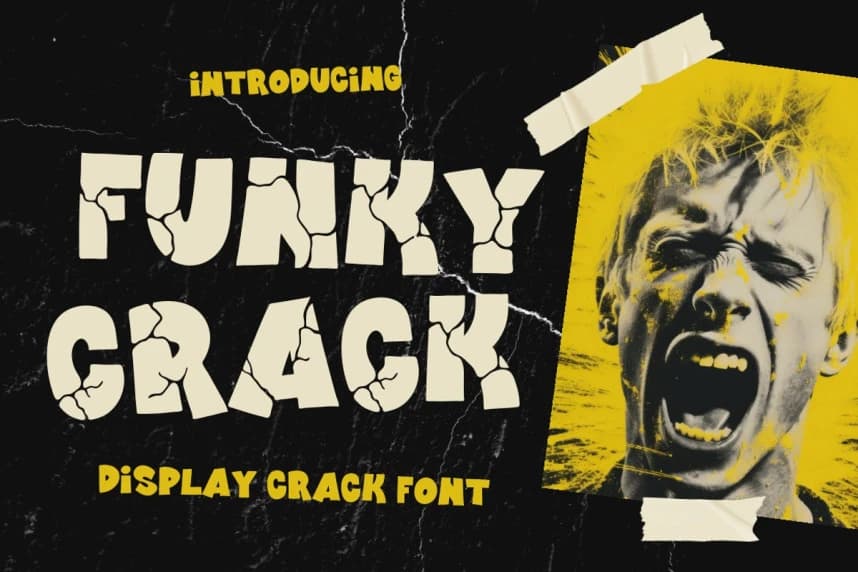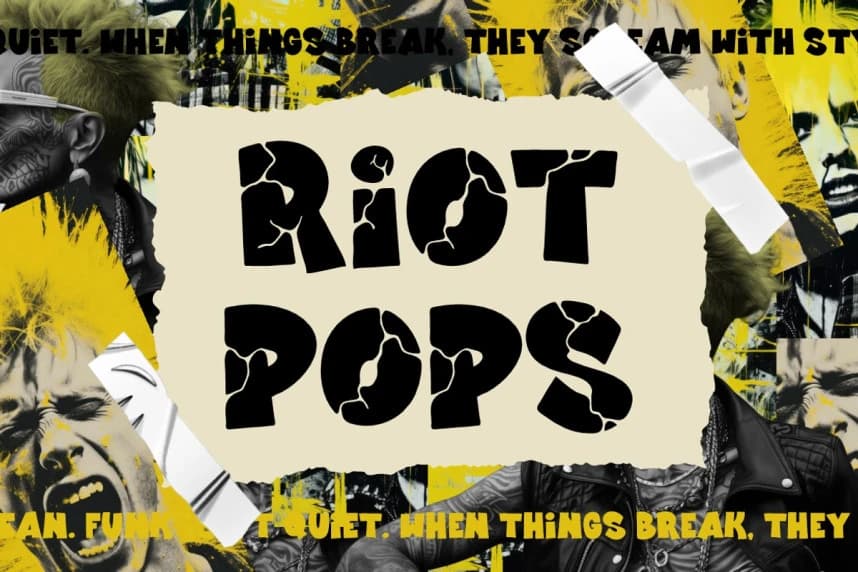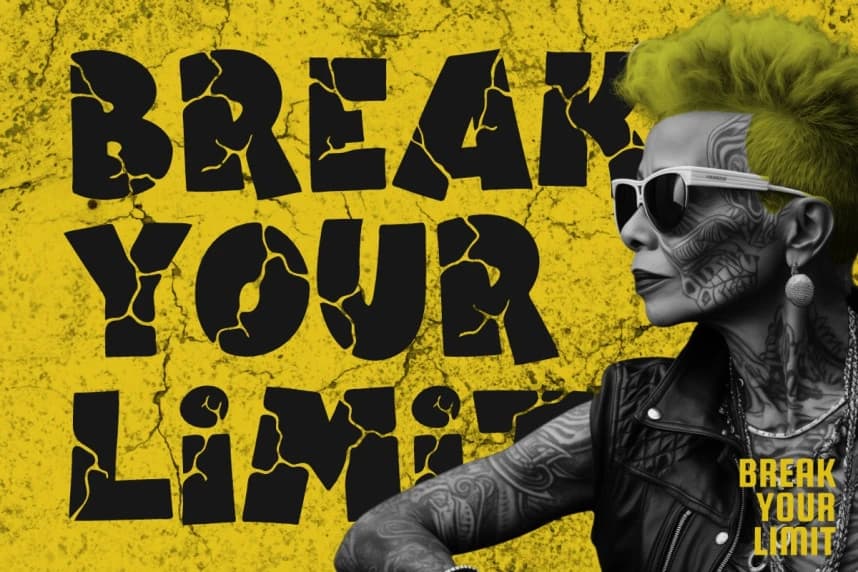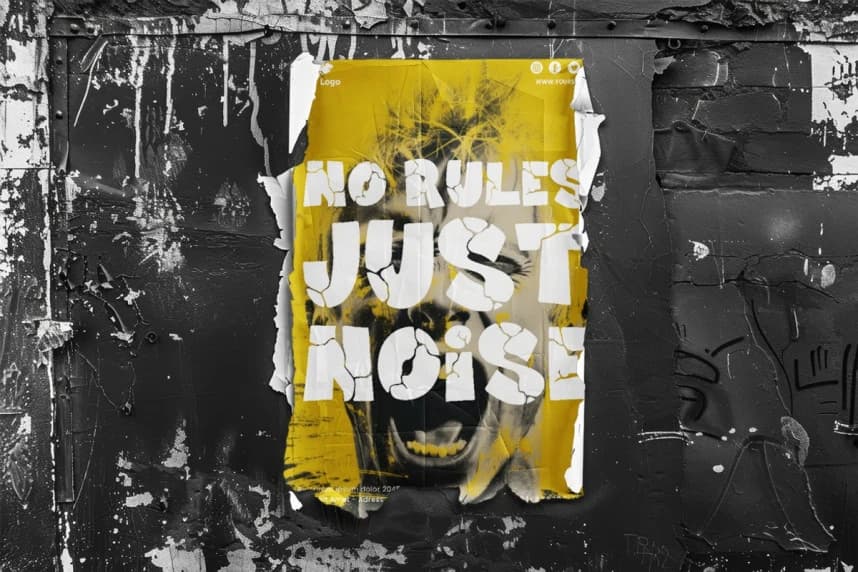
Funky Crack Font
Funk Crackle Font - Display Crack Font, tasarım kurallarını yıkmak için tasarlanmış güçlü bir gösteri yazı tipidir. Her harf, kırık, parçalanmış ayrıntılarla işlenmiştir; bu detaylar parçalanmış taşlar veya kırık duvarlar gibi görünür. Düzensiz dokusu asi bir enerji getirir.
Funk Crackle Font - Display Crack Font, tasarım kurallarını yıkmak için tasarlanmış güçlü bir gösteri yazı tipi. Her harf, çatlamış ve parçalanmış ayrıntılarla işlenmiş olup kırık taşlara ya da yıkılmış duvarlara benzer. Düzensiz dokusu asi bir enerji katar